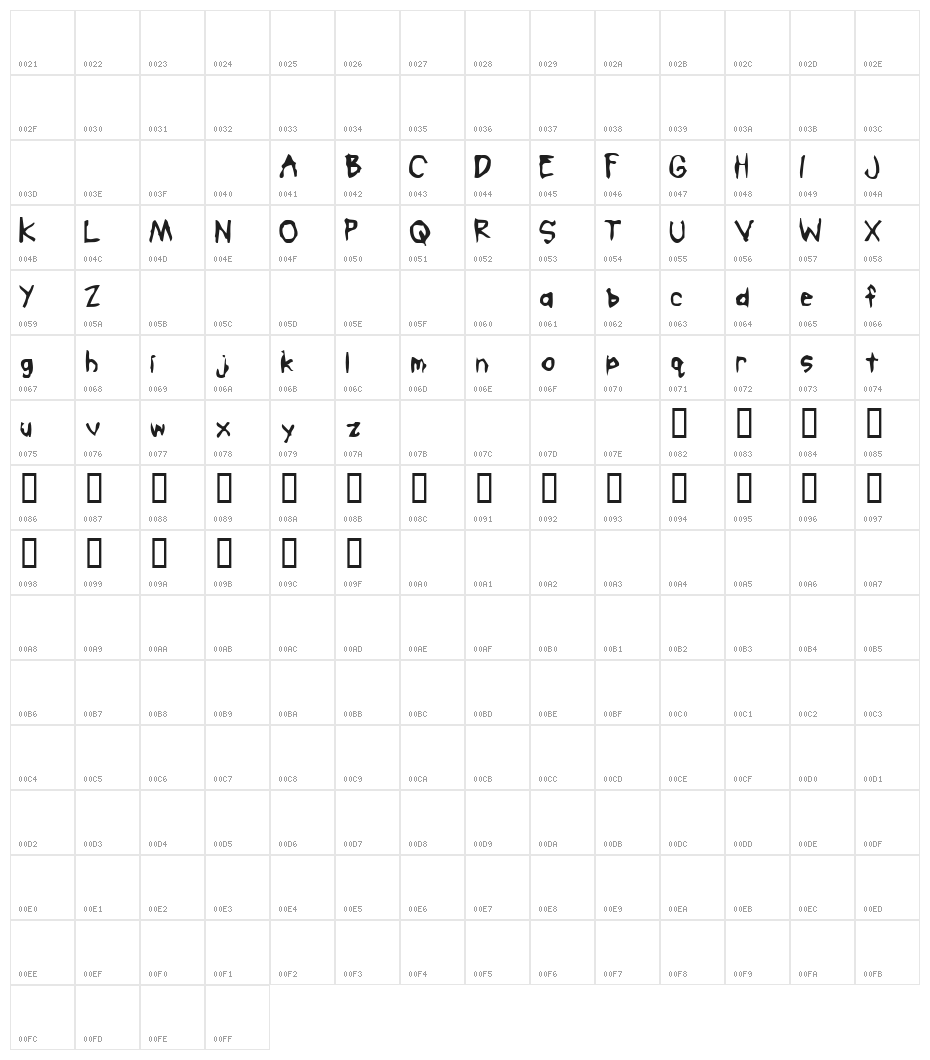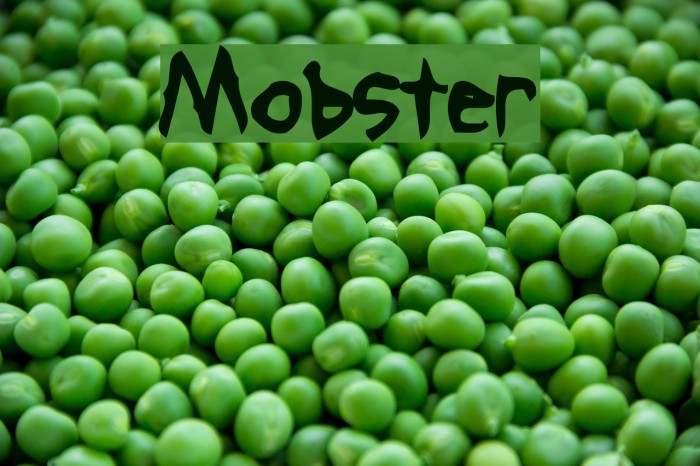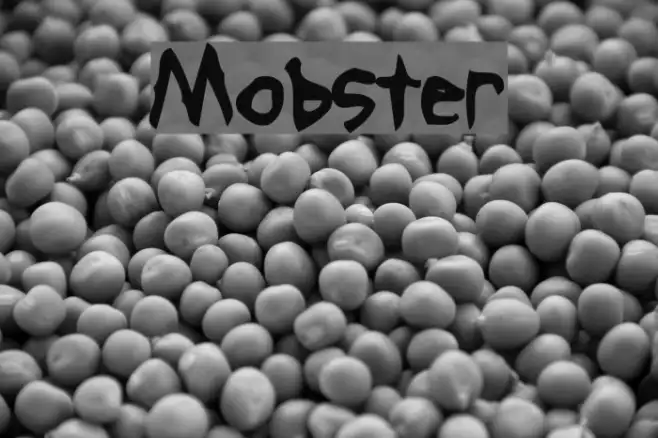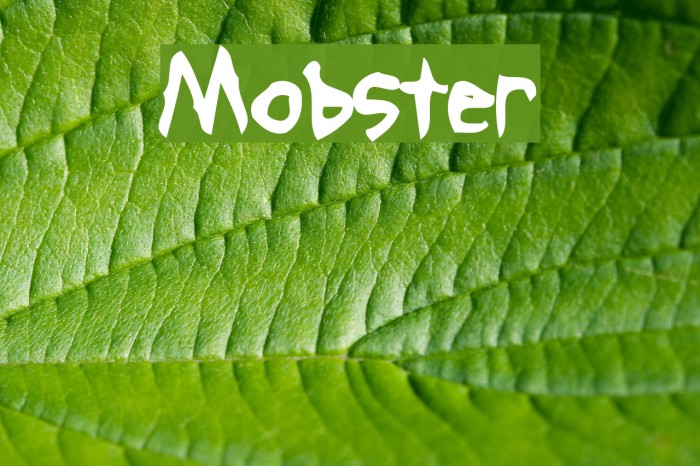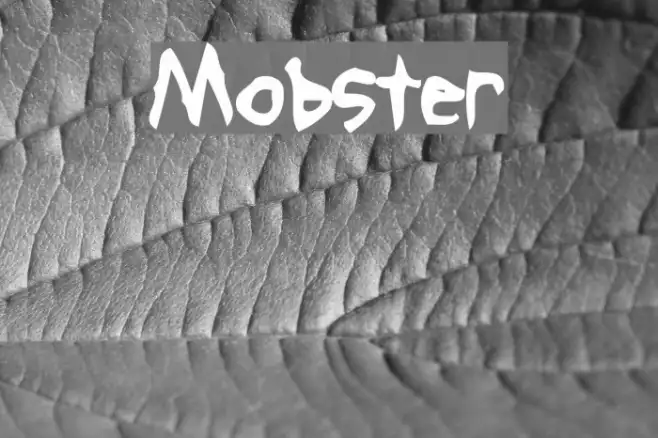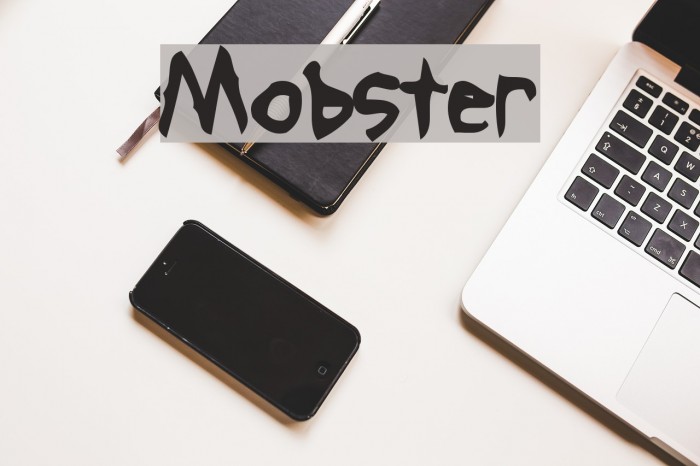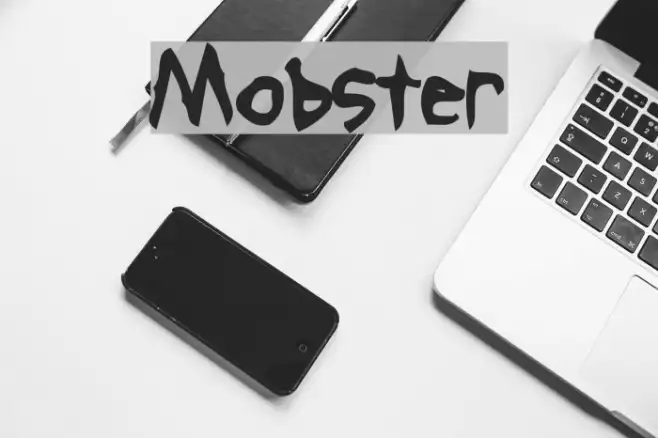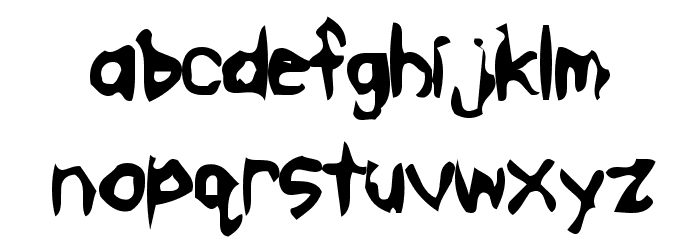
Mobster Font
| Stile generale | Playful and Cartoonish |
| Progetti proposti | Ideal for comic books, children's book covers, playful branding, and creative posters. |